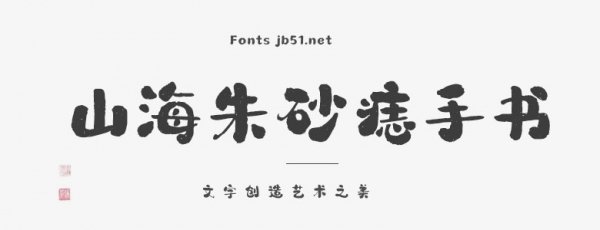
山海朱砂痣手書,是一款全新的卡通風(fēng)毛筆字體,包含漢字9169個(gè),符號(hào)200+個(gè)。該字體童趣可愛,結(jié)構(gòu)多變靈動(dòng),字形活潑清新,造型生動(dòng)有趣,具有靈活的適用性,天真俏皮又不失時(shí)尚感;同時(shí)以毛筆風(fēng)格的表現(xiàn)形式,使字體更別具一格,筆畫的飛白效果使字體的氣息更加流暢,筆畫間的關(guān)系密不可分,同時(shí)也增加了字體的自由俏皮之感。